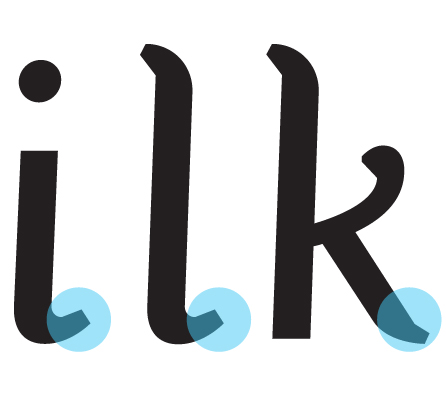
Desde la ciudad paraguaya de Asunción, Alejandro Valdez nos sorprende con la tipografia «Sarakanda» que esta creando con la intencionalidad de ayudar a los niños i niñas con problemas de dislexia a facilitar el aprendizaje de la lectura. El proceso parece de lo más riguroso y los resultados provisionales, son de lo mas alentadores. Deberemos seguir la pista de lo que vaya haciendo Alejandro.